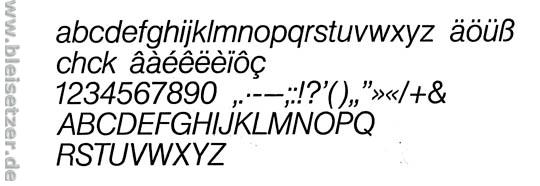
Hm. Ich würde auf eine dünne Helvetica Oblique tippen. Vielleicht light oder thin.
warte habe noch ein besseres schriftbild gefunden:
hmm werde aus whatthefont nicht schlau:
vielleicht könnt ihr mir weiterhelfen?
Nein, die Helvetica leicht kursiv ist es nicht.
Schau Dir mal das Gemeine "r" in der Vergrößerung an.
Aber sie kommt ihr sehr sehr nahe:
Den »Design Quarterly« – von dort hast Du doch den Ausschnitt, oder? – gibt es ja noch immer. Vielleicht könnten die Dir genauere Auskunft geben.